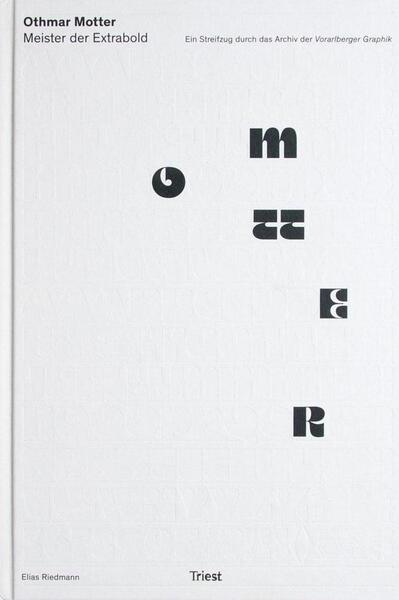
Othmar Motter, Meister der Extrabold
Tektura, Ombra, Corpus und Femina: Diese Schriften sind weltweit bekannt, doch ihr Gestalter, der Vorarlberger Grafikdesigner Othmar Motter, ist nur wenigen ein Begriff. Die vorliegende Monografie bringt Licht in Leben und Werk des 2010 verstorbenen Grafikdesigners. Der Autor – Elias Riedmann – stammt selbst aus Vorarlberg und absolvierte 2016 sein Grafikdesignstudium an der Universität für angewandte Kunst in Wien.
Die circa 350, durchgehend farbigen Seiten beginnen mit einem biografischen Überblick auf circa 20 Seiten. Den Rest des Buches nimmt dann eine umfangreiche Werkschau ein, die sich in die Bereiche »Schrift« und »Logo« gliedert. Das Buch schöpft dabei aus den circa 20 Schriften und um die 700 Signets, die Motter über die Jahre geschaffen hat. Die Werke werden nicht nur in ihrer endgültigen Version gezeigt, sondern oft auch in interessantem Skizzenmaterial aus dem Archiv Motters, das von seiner Familie weiter gepflegt wird.